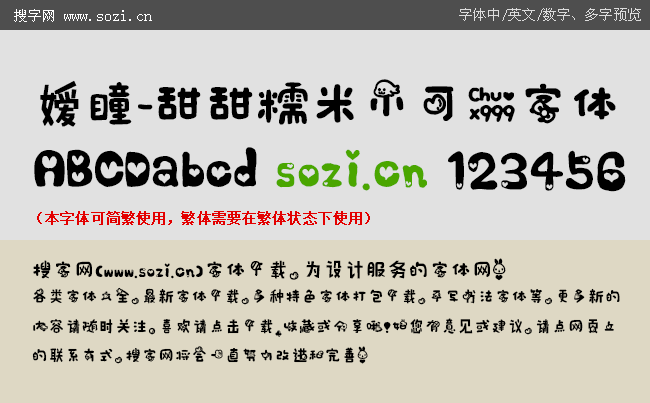
甜甜糯米小可愛字體
搜字網給大家提供一款很帶有手寫風格的卡通手機中文字體下載。修改者將它命名為甜甜糯米小可愛字體,這款手機字體是在仿照兒童手寫風格的卡通手寫字體筆畫間加上卡通圖案。即有卡通字體的趣味性,又有手寫字體的藝術性,真是童趣十足的一款字體,特別適合喜歡手機字體個性一些的朋友在手機上安裝使用。